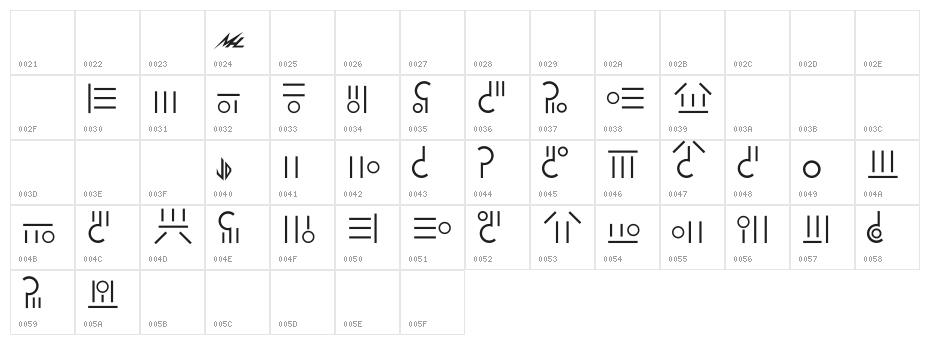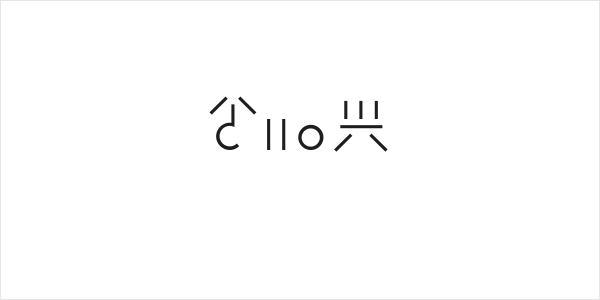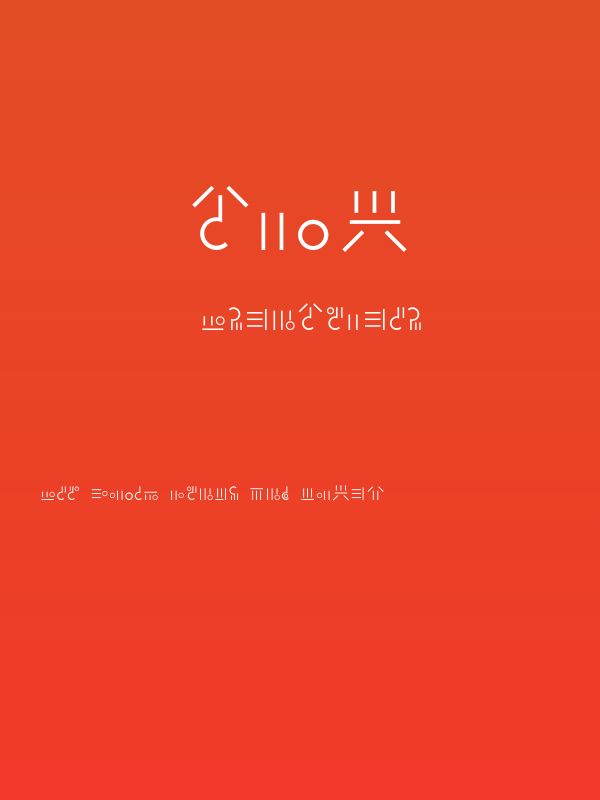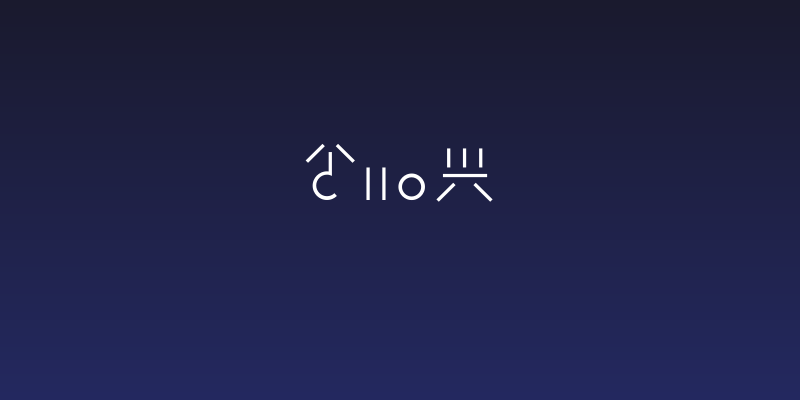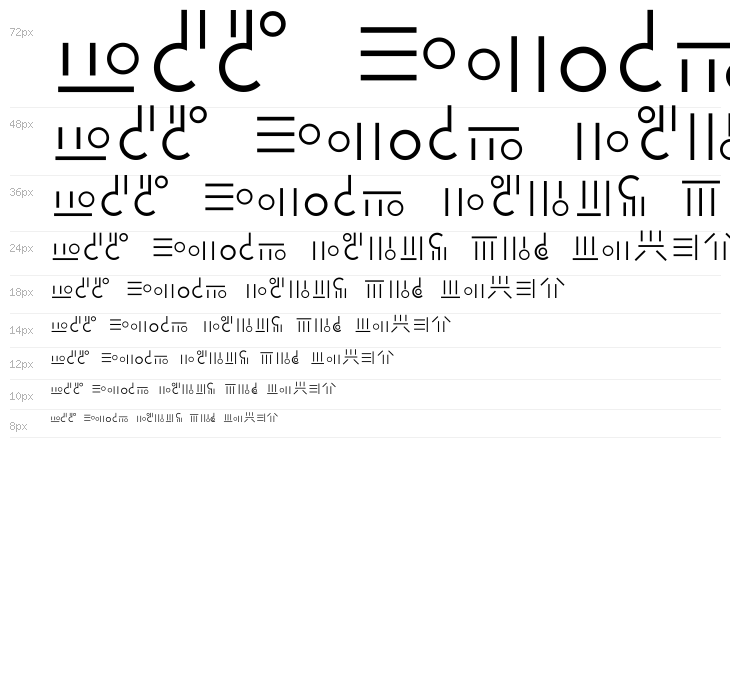
Gaim Font
✎ Futuristic
| Name | Gaim |
| Gewicht | Bold |
| Kategorien | Futuristic |
| Gesamtstil | Futuristic, Artistic |
| Anwendungsfall | Logos, Artistic projects, Sci-fi themes |
| Vorgeschlagene Projekte | Ideal for creative projects such as sci-fi themed designs, artistic posters, or unique branding elements. |